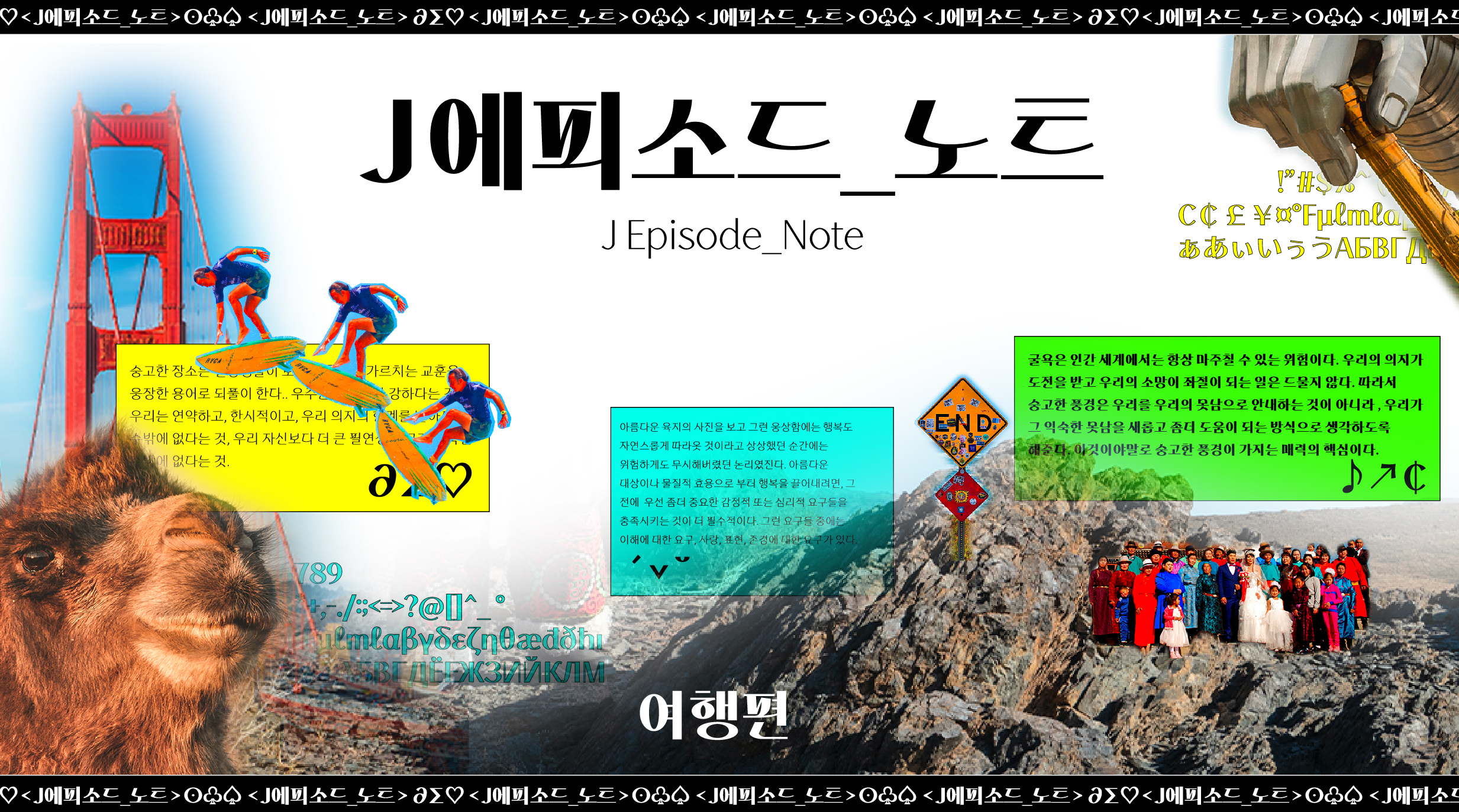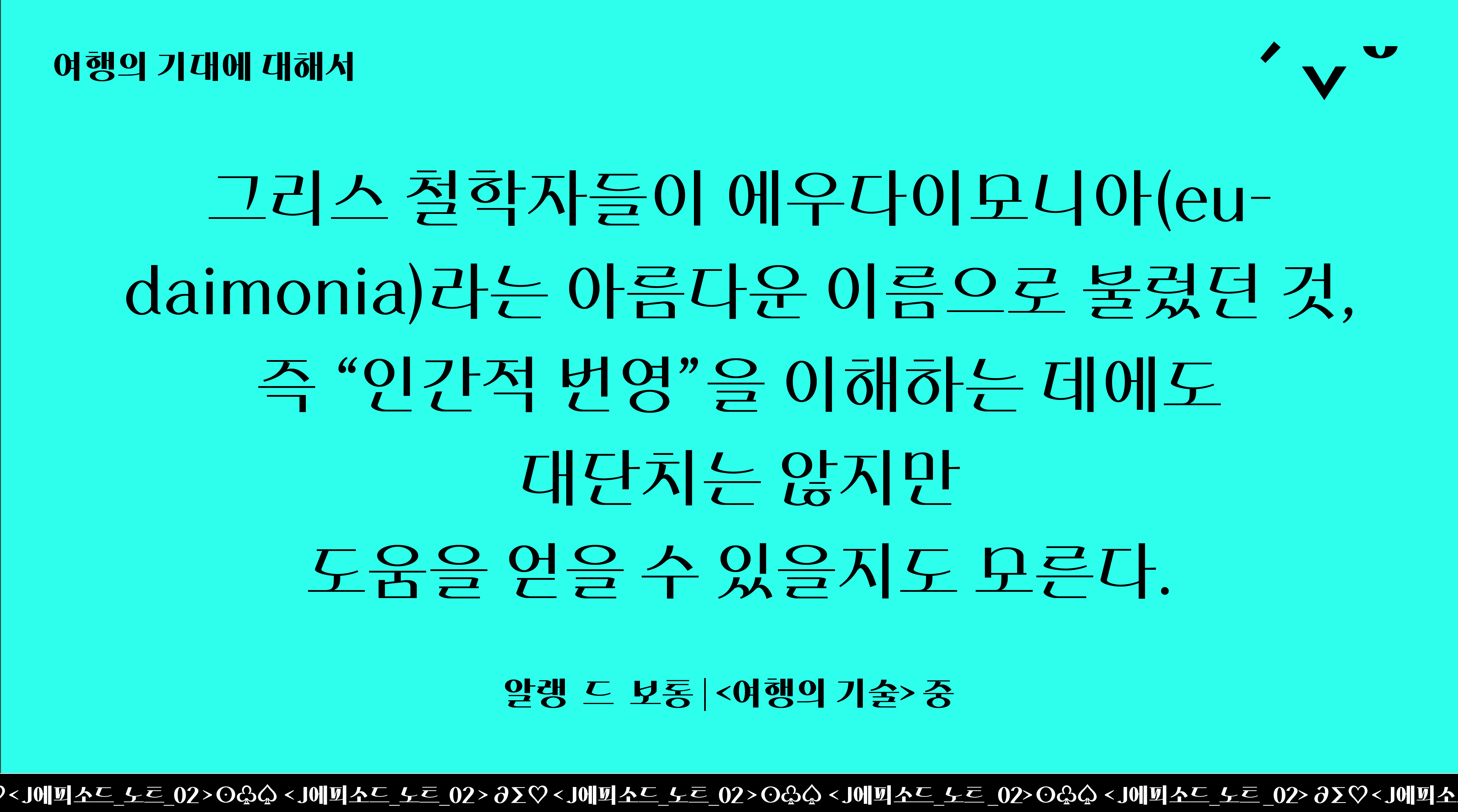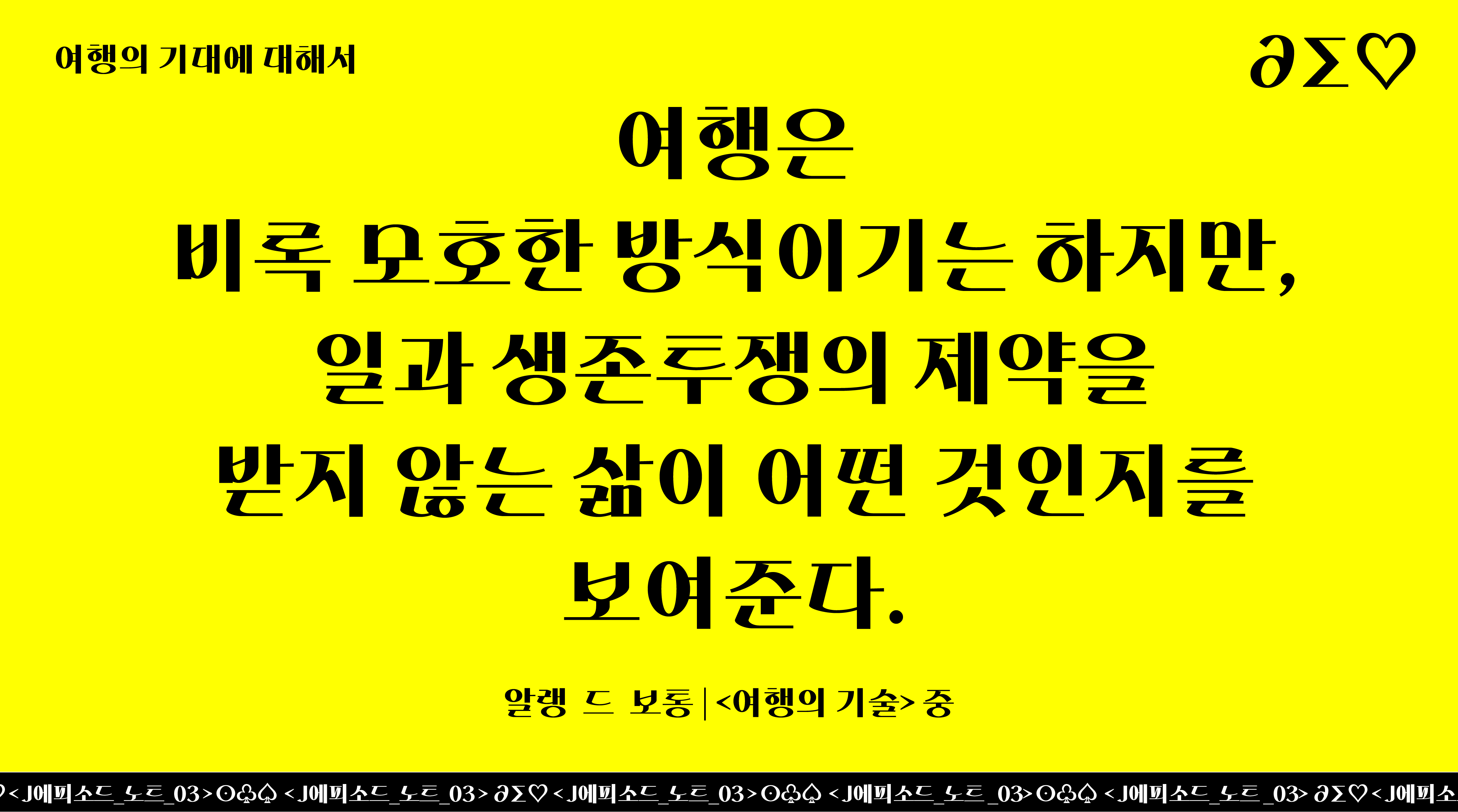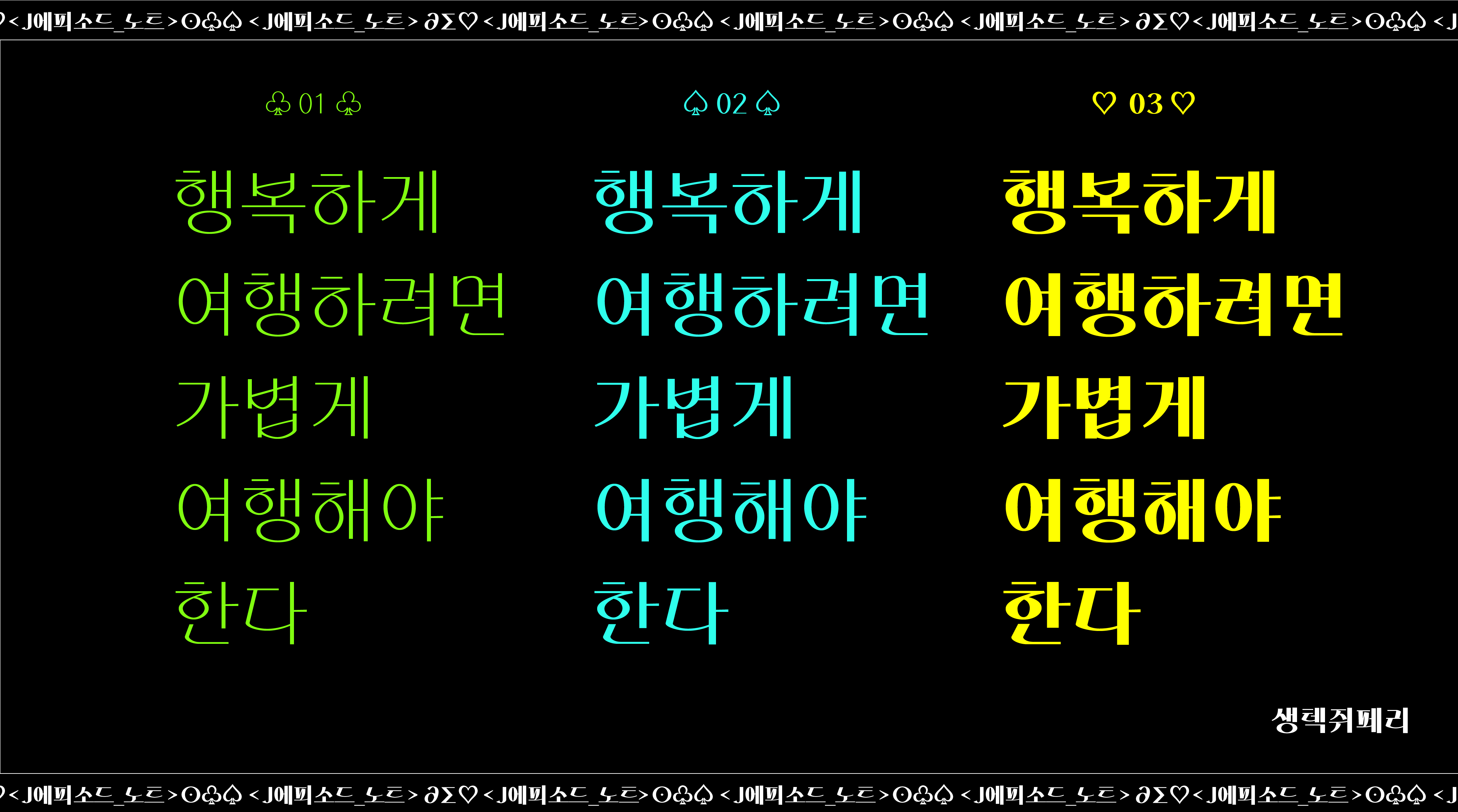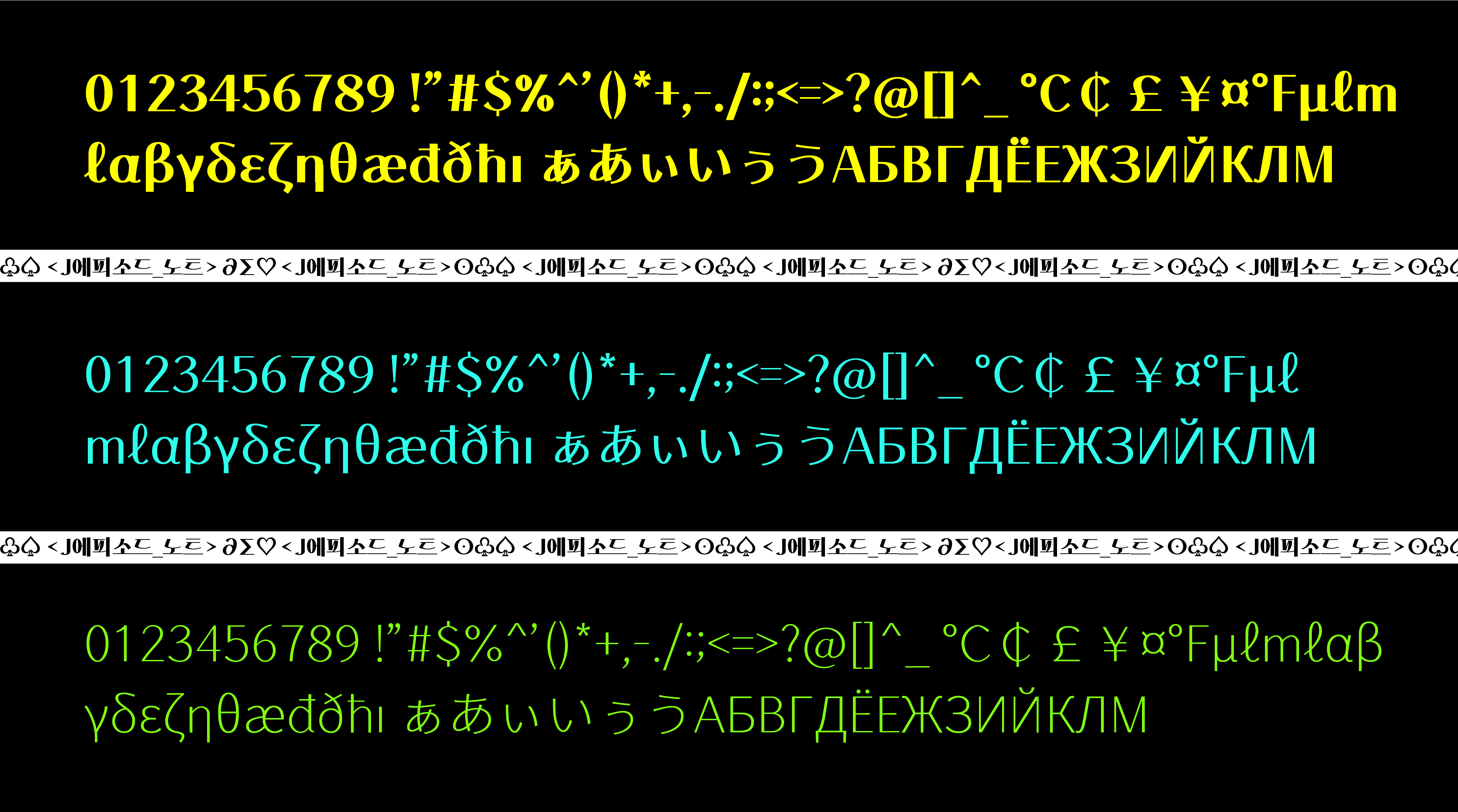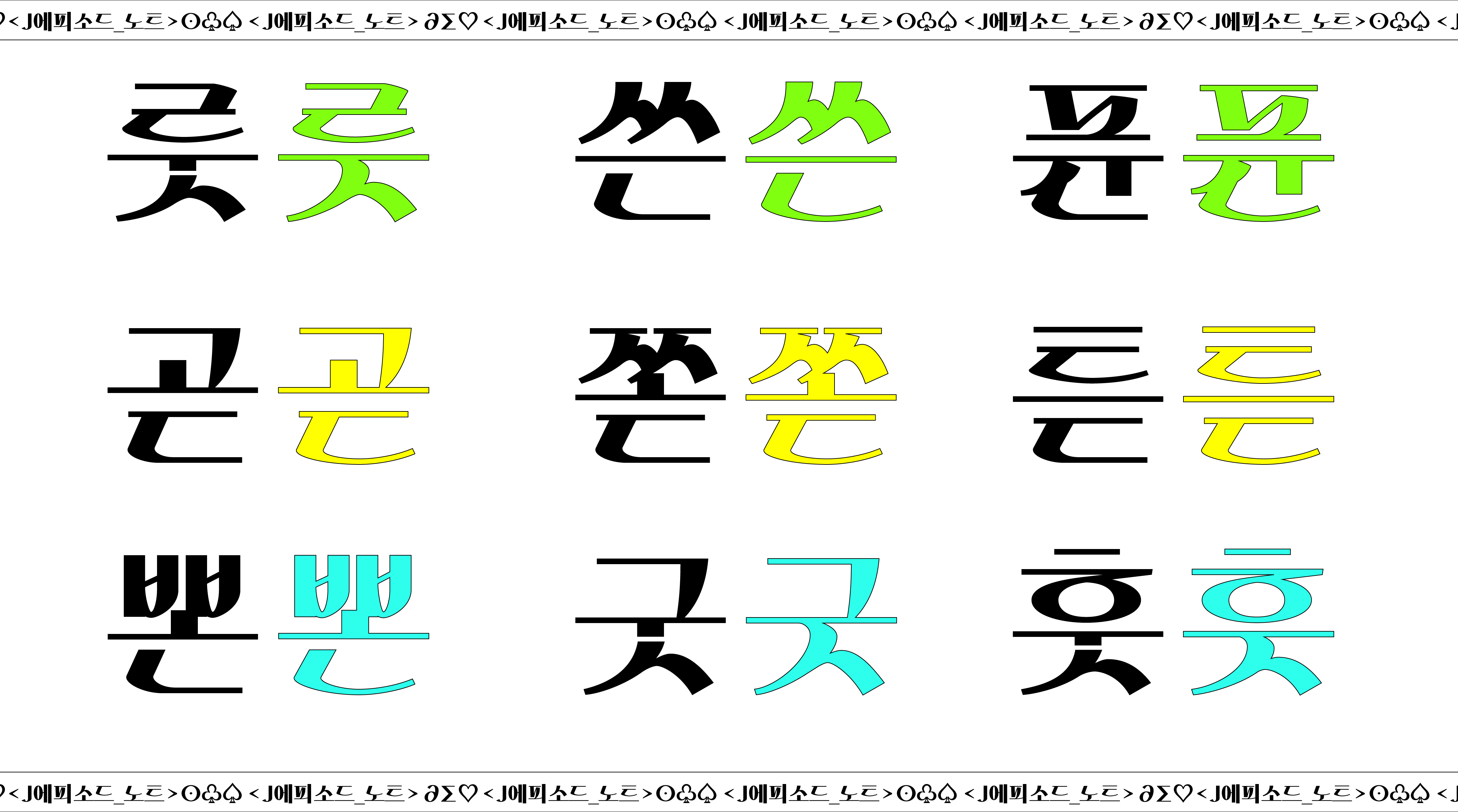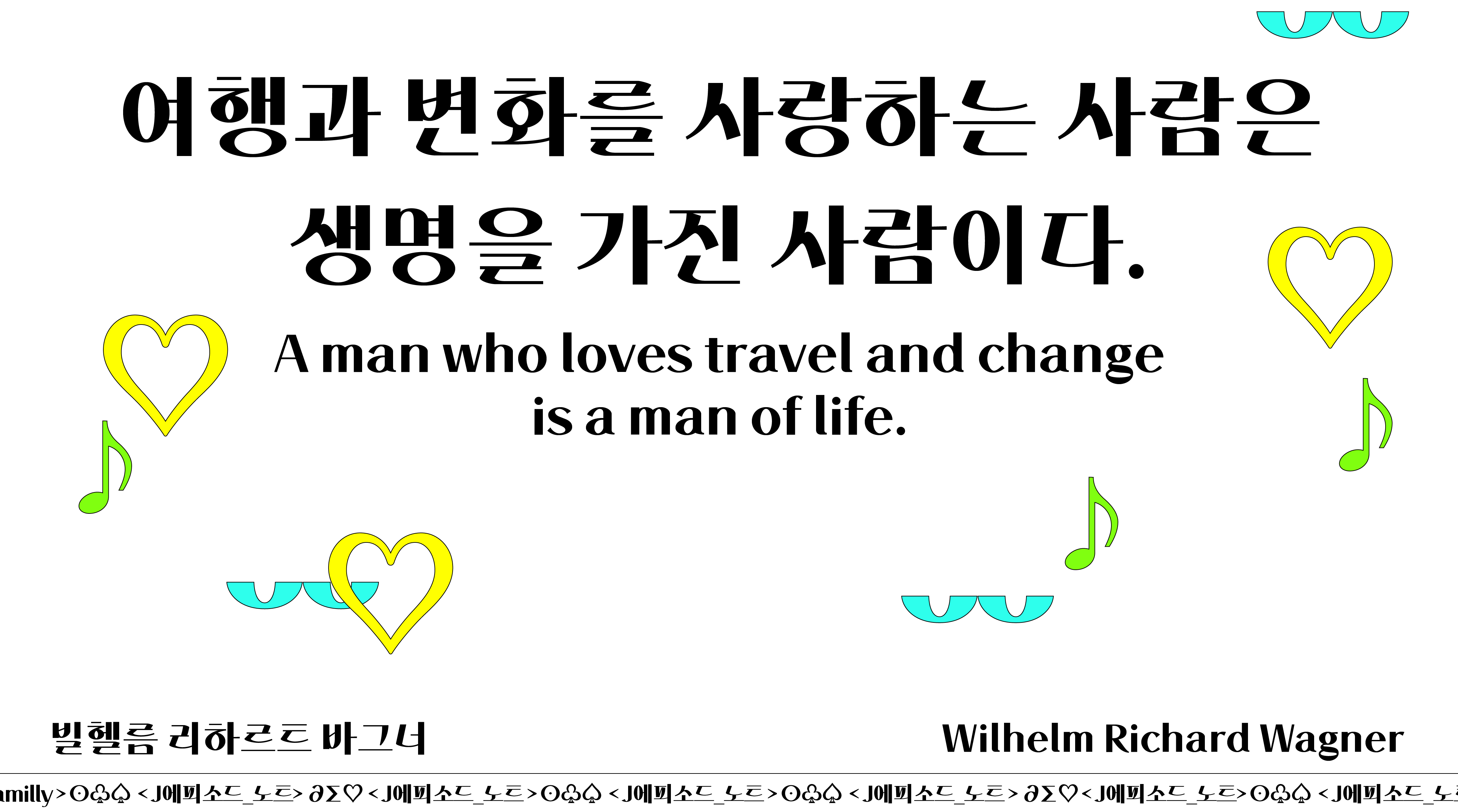
폰트 스펙
- 종수
3종
01, 02, 03
- 패밀리 여부
폰트 패밀리
- 글자수
한글 2,780자
라틴 94자
특수문자 986자
- 오픈타입 피처
세로꼴 종성 ㄴ 80자, 세로꼴 종성 ㄷ 28자, 세로꼴 종성 ㅅ 18자 추가
- 디자인 연도
2021
다양한 컨셉으로 활용이 가능하고 독특한 디자인 요소가 많은 서체 시리즈. 개성있는 디테일로 시각적 재미를 더하고 풍부한 이야기를 담을 수 있는 서체이다.
폰트 설명
<J에피소드_노트>는 “획 대비”와 “그래픽체” 안에서 손글씨의 필기감 디테일을 살린 디자인입니다.
패밀리로서의 통일감을 주기 위해 네모 고딕의 골격을 유지하되, 납작 팬으로 직접 써가며 필기 시에 표현될 수 있는 디테일을 더했습니다.
구성: 한글 2,780자 / 라틴 94자 / 기호활자 986자
총 3종으로 J에피소드_노트 01, 02,03 구성되며, 굵기가 더 굵어질수록 더 넓은 자폭을 가지고 있습니다.
한글 디자인 특징: J에피소드_노트는 에피소드 패밀리로서의 가로, 세로획의 큰 두께 대비와 네모 고딕 골격으로 일체감을 주었고, 필기감이 느껴지는 획으로 직선과 곡선의 조화에 중점을 이어갔습니다.
납작펜으로 필기 시의 흘림과 속도감을 반영한 자소 디자인이 J에피소드_노트의 대표적 특징입니다.
ㅍ, ㅎ 자음에서의 흘림과 ‘노’, ‘도’ ‘로’ ‘와’, ‘과’ 와 같은 세로 모임 꼴과 복합 모임 꼴에서 중성에서 속도감으로 인한 연결 디테일,
그리고 ‘웃’ 모임 꼴에서의 자연스러운 연결은 형태적으로 재미를 주는 요소입니다.
ㄱ, ㄹ, 꺾임을 주어 각도를 만들어 그에 따른 공간 분배에 신경을 썼습니다.
필기 시의 속도감을 느낄 수 있는 쌍시옷의 받침과 ‘벼’의 글자에도 주목해 주세요!
<J에피소드_노트>는 총 126개의 추가 글립을 제공합니다.
세로 모임 글자 종성 ㄴ -> 80개
세로 모임 글자 종성 ㄷ -> 28개
세로 모임 글자 종성 ㅅ -> 18개
작업 시에 글자의 형태를 선택하여 사용하세요 :)
굵기의 경우 두께별 사용 용도를 고려하여 설계했습니다. 01은 획 대비를 줄여 긴 문장에도 사용 가능할 수 있도록, 02, 03의 굵기는 개성 강하고 임팩트를 줄 수 있는 제목용으로 고려하여 작업했습니다.
라틴 디자인 특징: 납작 팬으로 쓴 콘셉트를 그대로 반영한 컨셉을 유지하였으며, 필력이 녹아있는 로만자 계열의 서체입니다.
국문의 획 특징을 반영하였고, 소문자의 경우 휴머니스트 계열의 산세리프로 작업했습니다.